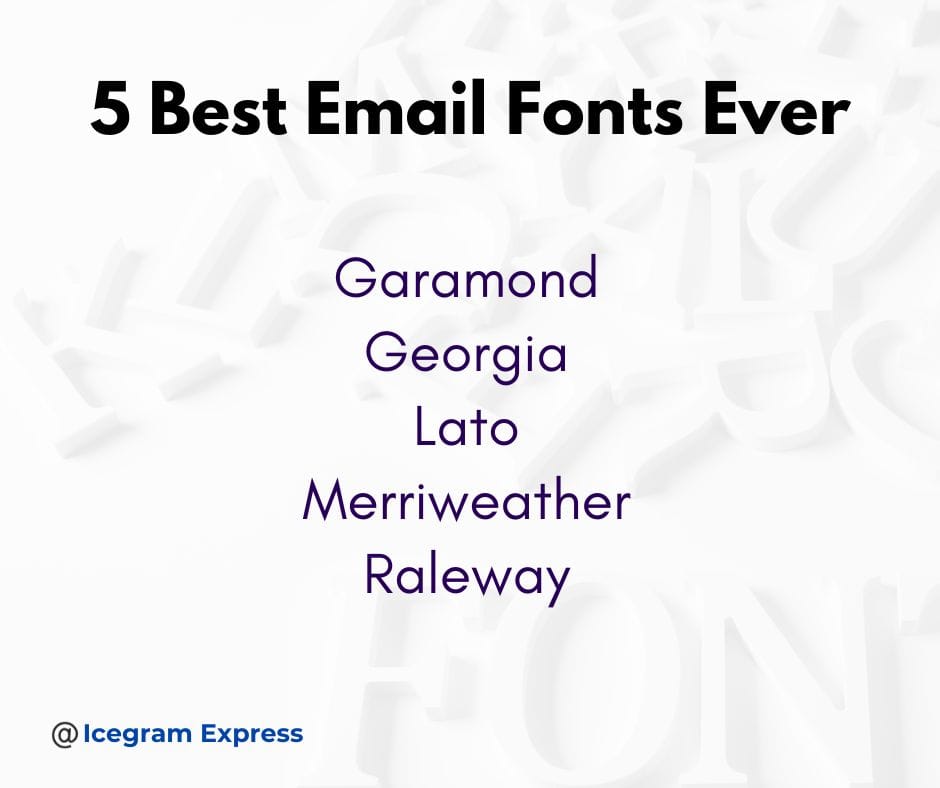
더 나은 전환을 위해 이메일 글꼴을 선택하는 방법은 무엇입니까?
게시 됨: 2024-01-17이메일이 마음에 들지 않아서 폐기한 적이 있습니까? 더 나은 전환을 위해 이메일 글꼴을 선택하는 방법을 알아봅시다.
이상하게 들리겠지만, 모든 마케터는 한번쯤은 경험해 본 적이 있을 것입니다. 일부 글꼴은 보기에 좋지 않고 관련성이 없다고 느껴집니다. 마케팅 담당자라면 이메일 마케팅에서 글꼴이 특별한 위치를 차지한다는 사실을 깨달았을 것입니다.
이제 이메일 글꼴이 최고였다면 얼마나 많은 거래를 성사시켰을지 상상해보세요. 또한, 유명 브랜드에서 글꼴을 변경한 경우도 본 적이 있을 것입니다.
이는 참여도와 브랜드를 진지하게 받아들이려는 사람들의 의지 모두에 영향을 미칩니다. 부적절한 글꼴은 최고의 마케팅에도 부정적인 인상을 남길 수 있습니다. 따라서 적절한 글꼴을 선택하는 것이 귀하의 의무가 됩니다. 전환율을 높이는 것 외에도 목표 시장에서 신뢰도를 구축합니다.
당신도 이것을 할 수 있습니다. 이 문서는 브랜드에 맞는 이메일 글꼴을 선택하는 데 도움이 됩니다.
이메일 타이포그래피: 이메일 글꼴을 선택하는 방법
가독성
가독성이 어떻게 전환율을 크게 높일 수 있습니까?
글꼴을 선택할 때 가독성은 청중의 참여를 유지하는 데 중요합니다. 형식, 내용, 제목과 같은 다른 요소가 독자의 관심을 끄는 동안 글꼴은 여전히 중요한 요소입니다.
최적의 가독성을 위해 모바일 장치를 포함한 모든 화면 크기에 적합한 글꼴을 선택하세요. 또한 포괄성은 브랜드가 다양한 청중에게 다가가고 충성도 높은 구독자를 확보할 수 있게 해줍니다. 따라서 글꼴은 난독증 환자와 시각 장애가 있는 사람도 읽을 수 있어야 합니다.
궁극적으로 이는 상호 작용 가능성과 전환율을 높일 것입니다.
명쾌함
깔끔하고 정돈된 글자로 된 이메일을 보는 것은 세상에서 가장 좋은 느낌입니다. 옳은?
글꼴에 글자와 획의 간격이 적절하면 이메일 내용을 더 쉽게 읽을 수 있습니다. 글꼴은 수신자가 큰 화면에서 읽든 작은 화면에서 읽든 해독이 가능해야 합니다.
또한 일부 글꼴은 작은 크기에서도 다른 글꼴보다 더 나은 선명도를 제공합니다. 따라서 난독증이 있는 독자와 시각 장애가 있는 독자에게 도움이 됩니다. 결국 이는 브랜드가 전환율을 높이는 데 도움이 됩니다. 따라서 브랜드 보이스를 보완하고 다양한 청중에게 다가갈 수 있는 이메일 글꼴을 선택하세요.
심리적 영향
특정 글꼴이 독자에게 특정한 느낌을 준다는 사실을 알고 계십니까? 이는 브랜드의 성장과도 연결된다.
글꼴은 이메일의 효과와 독자가 브랜드를 인식하는 방식에 큰 영향을 미칩니다. 권위를 전달하고 따뜻함, 친근함 등의 느낌을 불러일으키는 이메일 글꼴을 선택하는 것이 가장 좋습니다.
예를 들어 이것을 이해해 봅시다.
산세리프 글꼴은 모더니즘과 친근함의 메시지를 전달하는 데 유용합니다. 또는 세리프 글꼴은 세련미와 신뢰도를 줍니다. 스크립트 글꼴은 우아하고 재미있어 보일 수 있지만 전문적인 환경에서는 거의 사용되지 않습니다.
브랜드에 적합
좀 더 전문적인 옵션이 있는 반면 Curlz와 같은 캐주얼한 글꼴을 선택하시겠습니까?
전문적인 톤으로 얼마나 멀리까지 갈 수 있는지 놀라게 될 것입니다. 글꼴을 선택할 때 가장 먼저 고려하는 것은 청중의 어조입니다. 예를 들어, Z 세대는 장난스러운 분위기의 글꼴을 감상할 수 있습니다. 대조적으로, 나이가 많은 청중은 더 고전적인 글꼴을 선호할 수 있습니다.
또한 귀하의 브랜드에 적합한 글꼴은 귀하의 전문 분야에 따라 다릅니다. 귀하의 비즈니스가 놀이와 관련되어 있거나 어린이용 액세서리를 다루는 경우 더 굵은 이메일 글꼴이 적합할 수 있습니다. 브랜드가 기술과 같은 심각한 문제를 다루는 경우 기존 이메일 글꼴이 가장 적합한 선택입니다.
청중이 관련성 있는 이메일을 찾으면 전환율이 높아질 것입니다.
줄 간격
줄 간격이 자료의 가독성에 큰 영향을 미친다는 것은 명백하지 않습니까?
줄 간격은 큰 크기에서는 큰 영향을 미치지 않습니다. 그러나 크기가 커질수록 글자와 줄 사이의 간격이 줄어들어 텍스트를 이해하기 어려울 수 있습니다. 긴 이메일 내용에는 큰 글꼴 크기가 적합하지 않습니다. 일부 글꼴은 텍스트가 비좁아 보이기 때문에 작은 크기에서는 사용하기에 적합하지 않습니다. 언젠가는 전환율이 감소하고 브랜드 참여도에 부정적인 영향을 미칠 수 있습니다.
이러한 실수를 방지하려면 작은 크기와 모바일 장치에서 글꼴이 얼마나 잘 읽히는지 검사하세요. 글자는 겹치지 않아야 하며, 올바른 줄 간격으로 가독성이 높아야 합니다. 굵은 글꼴과 기울임꼴 글꼴의 적응성을 확인하는 것도 중요합니다.
이러한 테스트를 사용하면 이메일에 적합한 이메일 글꼴을 선택하고 변환이 개선되는 것을 확인할 수 있습니다.
A/B 테스트
이메일 글꼴을 무작위로 선택하는 것은 해로울 수 있습니다. 글꼴 또는 테스트된 글꼴을 조합하는 것이 결과를 확인하는 더 좋은 방법일 수 있습니다. 글꼴은 청중과 관련이 있어야 하며 귀하의 비즈니스를 나타내야 합니다.
다양한 글꼴 조합을 시도하여 브랜드 목소리에 가장 적합한 글꼴 조합을 찾아보세요. 어떤 것이 더 나은 결과를 가져오는지 확인하고 타겟 고객이 결정하도록 하세요. 전환율을 높이고 헌신적인 고객을 유치하려면 눈에 띄는 개인화된 경험을 제공해야 합니다.
따라서 이메일 글꼴 스타일을 선택하기로 결정한 경우 분할 테스트 방법을 사용하십시오. 귀하의 이메일 마케팅 전략에 이상적인 것을 선택하십시오.
향상된 전환율을 위해 이메일 글꼴을 선택하는 방법은 무엇입니까?
전 세계 청중에게 영향을 미치려면 오류가 용납되지 않습니다. 각 글꼴에는 고유한 미적 매력이 있으므로 올바른 이메일 글꼴을 선택하는 것이 중요합니다. 적절하게 사용하면 사람들의 마음에 지속적인 인상을 남길 수 있습니다. 궁극적으로 이는 이메일 개봉률이 높아짐에 따라 전환율이 증가하는 결과를 가져옵니다.
전환율을 높이는 데 도움이 될 수 있는 다양한 이메일 글꼴에 대해 알아보세요.
아리알의 힘
첫 번째 Microsoft 문서를 작성할 때 어떤 글꼴을 사용하셨나요? 아직도 기억하시나요?
이메일 마케팅 여정을 시작하면 Arial이 기본 글꼴이 됩니다. 이는 여전히 Gmail의 기본 글꼴로, 다른 산세리프 서체 중에서 이러한 영예를 얻었습니다.
그렇다면 왜 Arial이 Gmail의 기본 글꼴일까요?
부드러운 곡선과 둥근 획은 Arial을 다른 글꼴과 구별합니다. 즉, 뛰어난 이해력 때문에 바람직합니다. 간격이 균일하고 세련되고 현대적인 디자인을 갖추고 있어 이메일 헤드라인과 텍스트에 가장 적합한 옵션입니다.
따라서 높은 가독성과 인본주의적인 특성으로 인해 독자는 브랜드에 관심을 갖게 됩니다.
유명한 베르다나
산세리프 계열인 Verdana는 넉넉한 너비와 공간으로 독특한 스타일을 제공합니다. 획(대각선, 곡선, 직선)이 보기 좋고 정확하며 단순하여 고해상도 화면에 적합합니다. 소문자, 대문자, 숫자의 독특한 스타일은 높은 가독성을 제공합니다.
Verdana가 시각 장애가 있는 사람들에게 도움이 된다는 것을 알고 계셨나요?
예, 매끄러운 곡선과 두꺼운 획이 있는 Verdana 글꼴은 시각 장애가 있는 사람들이 쉽게 접근할 수 있도록 해줍니다. 이는 브랜드가 다양한 구독자에게 다가갈 수 있는 기회를 열어줍니다. 이를 통해 Verdana는 브랜드의 전환율을 높일 가능성을 높일 수 있습니다.
헬베티카의 매력
Helvetica의 매력은 전 세계의 마케터들을 매료시킵니다. 1950년대와 1960년대에 스위스 디자이너들은 네오그로테스크한 디자인인 Helvetica 또는 Neue Haas Grotesk를 만들었습니다. 그것은 20세기에 널리 퍼졌습니다. 치밀하고 견고한 외관과 특이한 스트로크로 유명합니다.
멀리서도 가독성이 높아 다양한 분야에서 활용하기 적합합니다. 여기에는 마케팅, 비즈니스, 판촉 및 프리젠테이션이 포함됩니다. 그 다양성에는 다음이 포함됩니다.
- 로고 디자인
- 포스터, 배너
- 도로 표지판
- 명함 또는 초대장
- 브랜딩 프로젝트
- 블로그 테마 디자인
- 소셜 미디어 게시물
- 브로셔
간단한 텍스트, 짧거나 긴 단락, 텍스트 본문에 이메일 글꼴을 선택하려면 Helvetica가 적합합니다. 독자가 끝까지 스크롤하도록 유도하여 전환율의 가능성을 높입니다.
조지아의 유동성
조지아주가 공식 문서를 작성할 때 그토록 존중하는 이유는 무엇입니까? 궁금하지 않으세요?
Georgia 글꼴은 가독성과 매력을 제공하면서 텍스트에 개성을 더해줍니다. 저해상도 화면에서도 선명함을 전달하고, 작은 크기에서도 친근감을 선사합니다. 서체 디자이너 매튜 카터(Matthew Carter)가 만든 이 글꼴은 텍스트의 우아함을 강조합니다.
Georgia 글꼴은 컴퓨터 화면(작은 화면)과의 호환성이 높습니다. 이탤릭체로 효과적인 글쓰기와 인쇄 선명도를 보여줍니다. 이러한 모든 속성은 이메일 복사에 가장 선호되는 선택 중 하나입니다.
타호마의 우아함
아시다시피 Tahoma는 특히 디지털 콘텐츠를 처리하도록 설계되었습니다.
Tahoma는 Matthew Carter가 디자인한 또 다른 매력적인 산세리프 서체입니다. 이 서체는 다양한 크기로 회전하고 크기를 조정할 수 있으므로 트루타입 글꼴입니다. 프레젠테이션과 사용자 인터페이스에서 일반적입니다. 그 결과 기술계에서는 '전문적인 텍스트' 스타일로 유명하다.
Tahoma와 Verdana가 기술 세계에서 인기 있는 글꼴이라는 점은 주목할 만합니다. 이들의 차이점은 Tahoma가 본문 텍스트에 유용하다는 점입니다. 이와 대조적으로 Verdana는 제목, 헤드라인 및 기타 큰 서체에 유용합니다.
루시다의 특기
Lucida는 전환율을 높이는 데 도움이 되는 Sans 계열의 독특한 글꼴입니다. 방법을 아시나요?
이메일 글꼴 선택 방법 – 마무리
글꼴은 세련되고 권위 있고 재미있을 수 있습니다. 모든 것은 타겟 고객, 목적 및 브랜드 목소리를 기반으로 합니다.
특정 글꼴은 다양한 독자에게 뚜렷한 감정을 불러일으킨다는 점을 명심하세요. 올바른 글꼴에는 글꼴을 강화하거나 감소시키는 힘이 있습니다. 이메일에 적합한 글꼴을 선택하는 것이 중요한 과정이라고 말하는 것이 타당합니다.
특정 글꼴을 선택할 때 눈에 띄고 새로운 고객을 유치하려면 신중한 고려가 필요합니다. 결국 독자에게 지속적인 인상을 남기고 전환율을 높입니다.